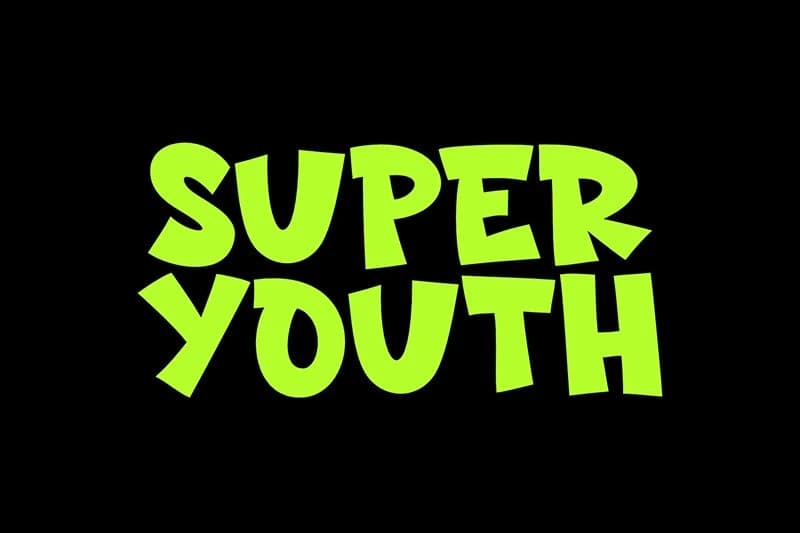
Super Youth Font
Super Youth Font, herhangi bir tasarıma eğlenceli ve canlı bir kişilik katmak amacıyla tasarlanmış, oyuncu ve dikkat çekici bir çizgi film tarzı gösterim yazı tipidir. Kalın, yuvarlak hatlı ve biraz düzensiz harf biçimlerine sahip olan bu yazı tipi, oyuncu ve enerjik bir görünüm yaratır ve bu da onu
Super Youth Font, herhangi bir tasarıma eğlenceli ve canlı bir kişilik katmak için tasarlanmış, oyunbaz ve dikkat çekici bir karikatür tarzı gösterim fontudur. Kalın, yuvarlak hatlı ve hafif düzensiz harf biçimlerine sahip olan bu font, büyüleyici ve enerjik bir görünüm yaratır; bu da onu yaratıcı ve samimi projeler için mükemmel kılar.